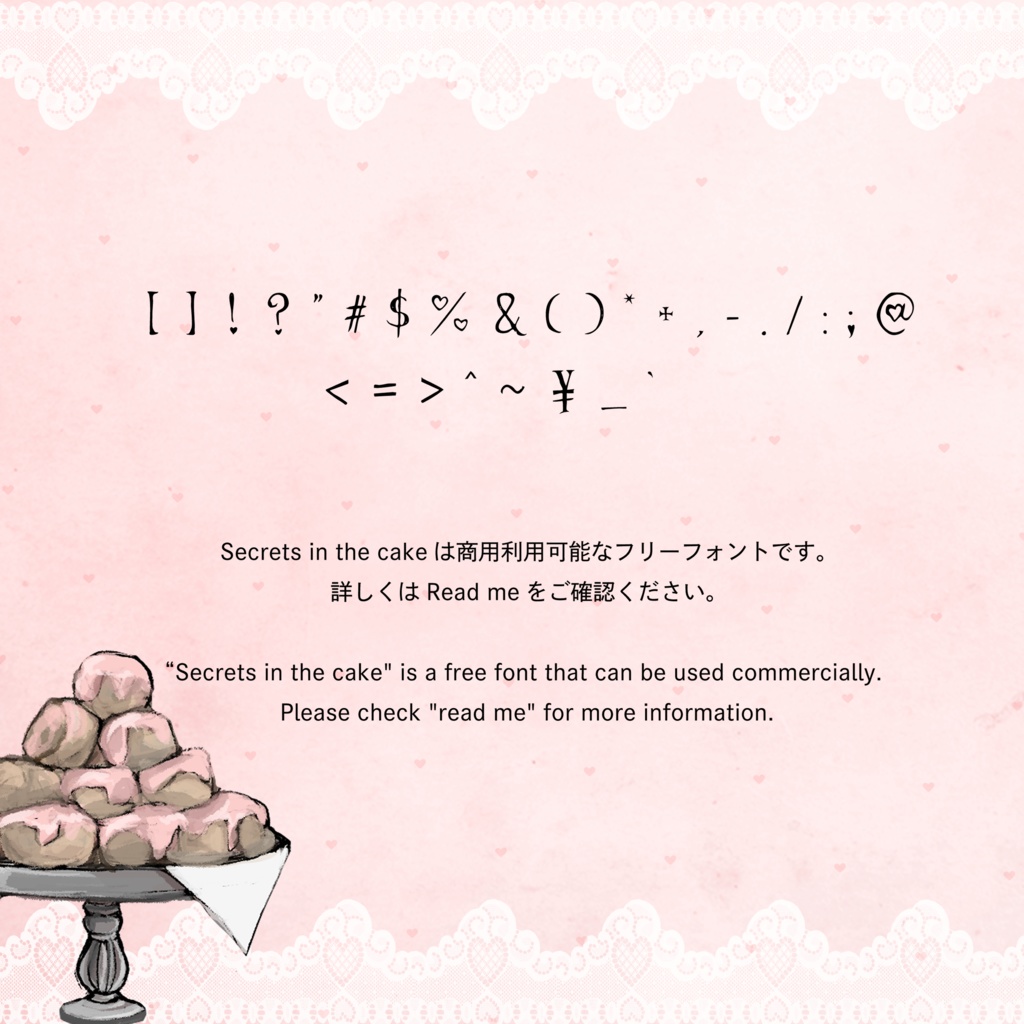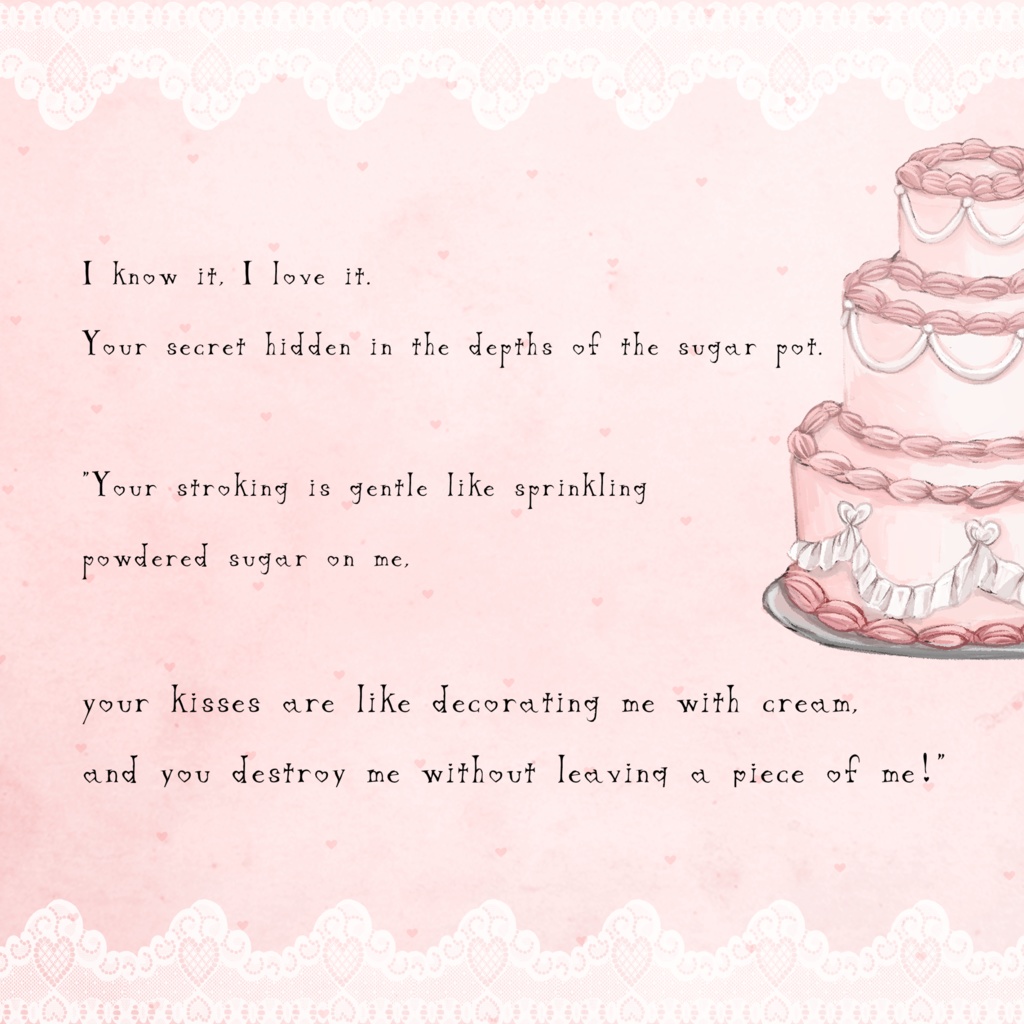
【フリーフォント】Secrets in the cake
yumeko(@devilxkid)の手書き欧文フォントです。 少女の秘密をテーマにガーリーでレトロなシルエットを意識し、文字の一部にハートをあしらっています♡🕯 収録文字 ! " # $ % & ' ( ) * + , - . / 0 1 2 3 4 5 6 7 8 9 : ; < = > ? @ A B C D E F G H I J K L M N O P Q R S T U V W X Y Z [ \ ] ^ _ ` a b c d e f g h i j k l m n o p q r s t u v w x y z { | } ~ 利用規約 個人、商用利用可能なためご自由にお使いください。 著作権は放棄しておりません。 ご利用の際に報告やクレジット表記は必要ありませんが、頂けると嬉しいです! 詳しい規約はテキストファイルの"Read me”をご確認ください。 Handwritten European font by yumeko (@devilxkid). The theme is a girl's secret, with a girly, retro silhouette in mind, and a heart as part of the text ♡🕯. Terms of Use Please feel free to use this information for personal and commercial use. Copyrights are not waived. No report or credit is required for use, but we would appreciate it if you could give us one! Please see “Read me” in the text file for detailed terms and conditions. The company also offers its products in font space for overseas customers. Click here for URL→https://www.fontspace.com/secretsinthecake-font-f138827